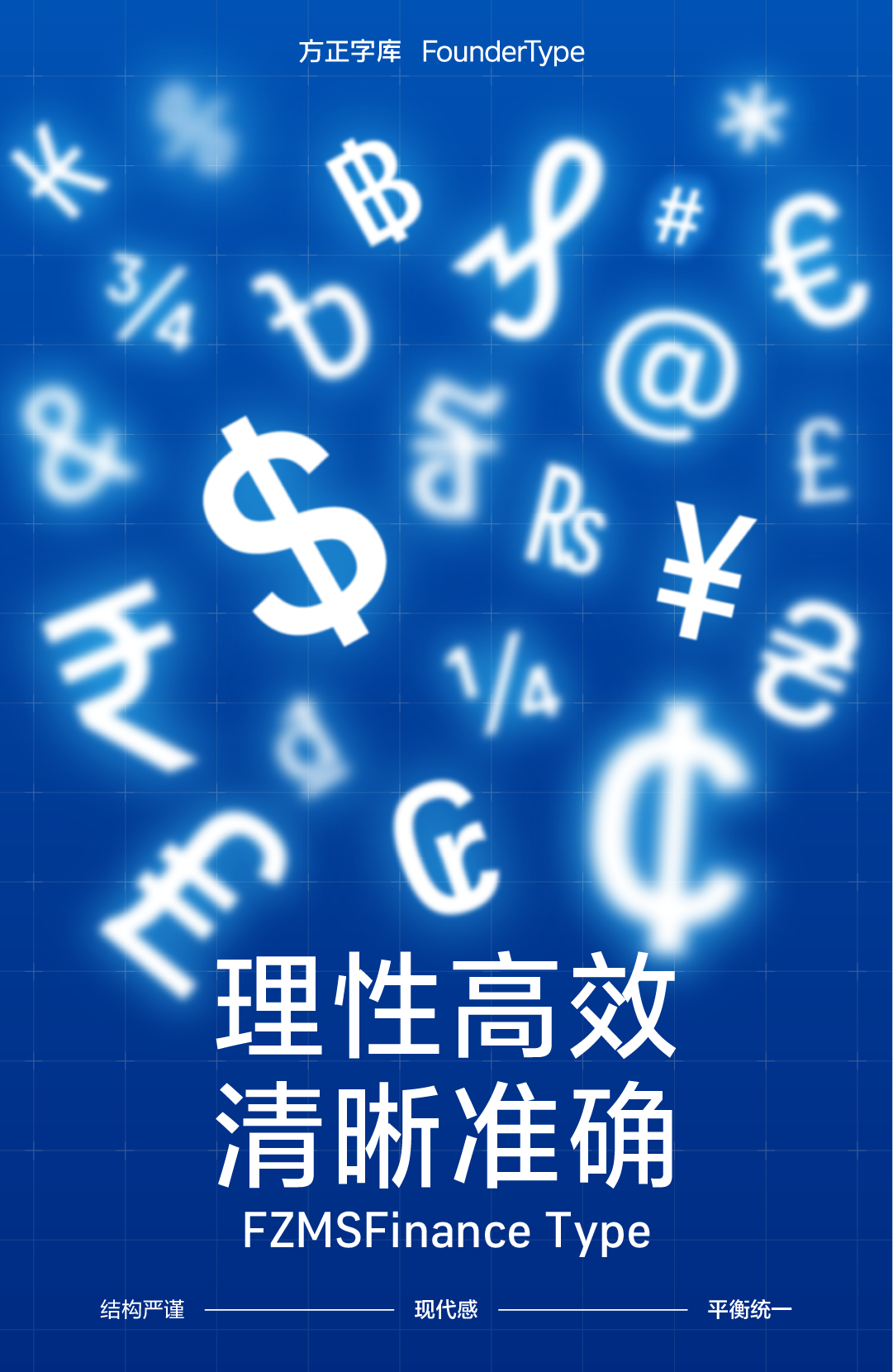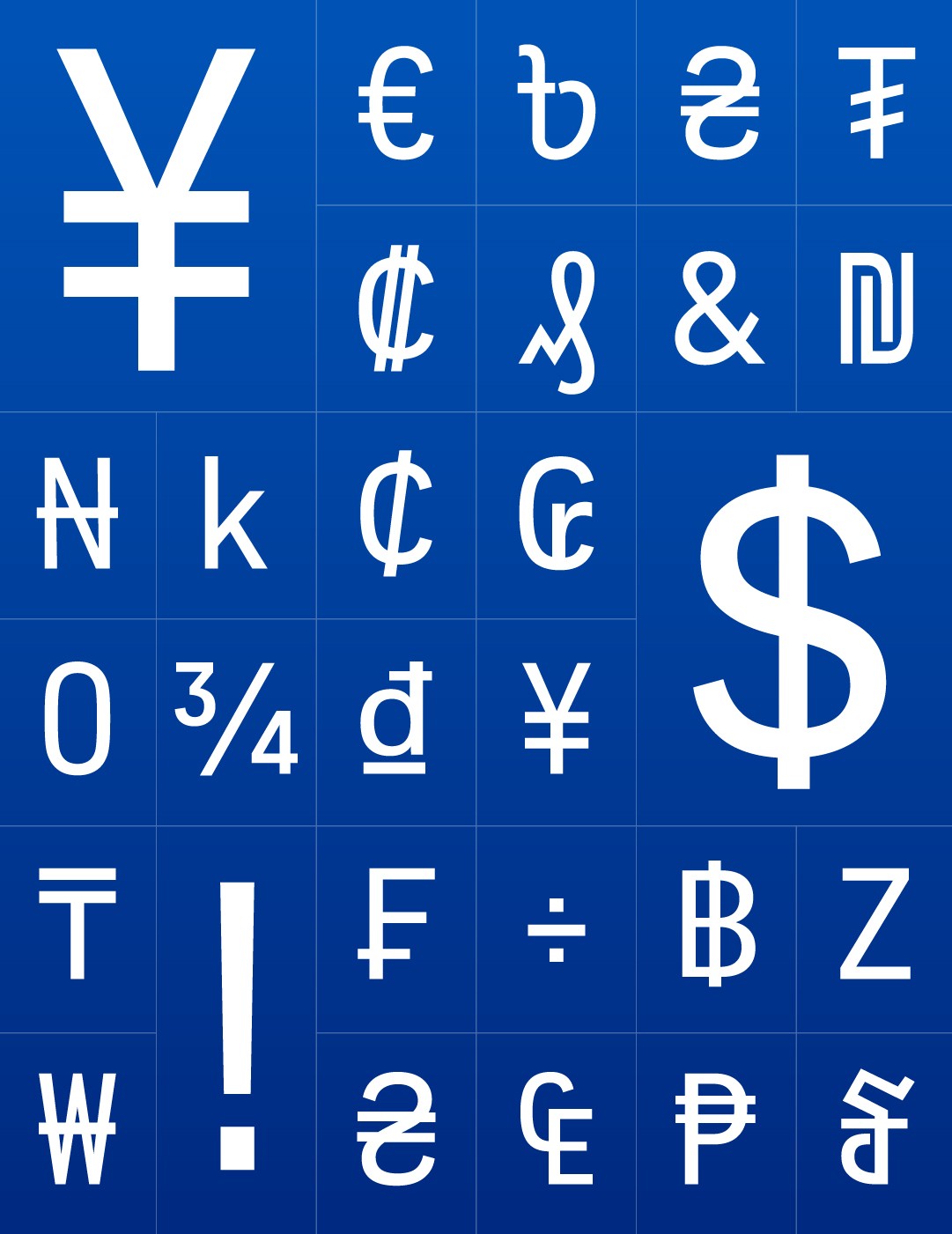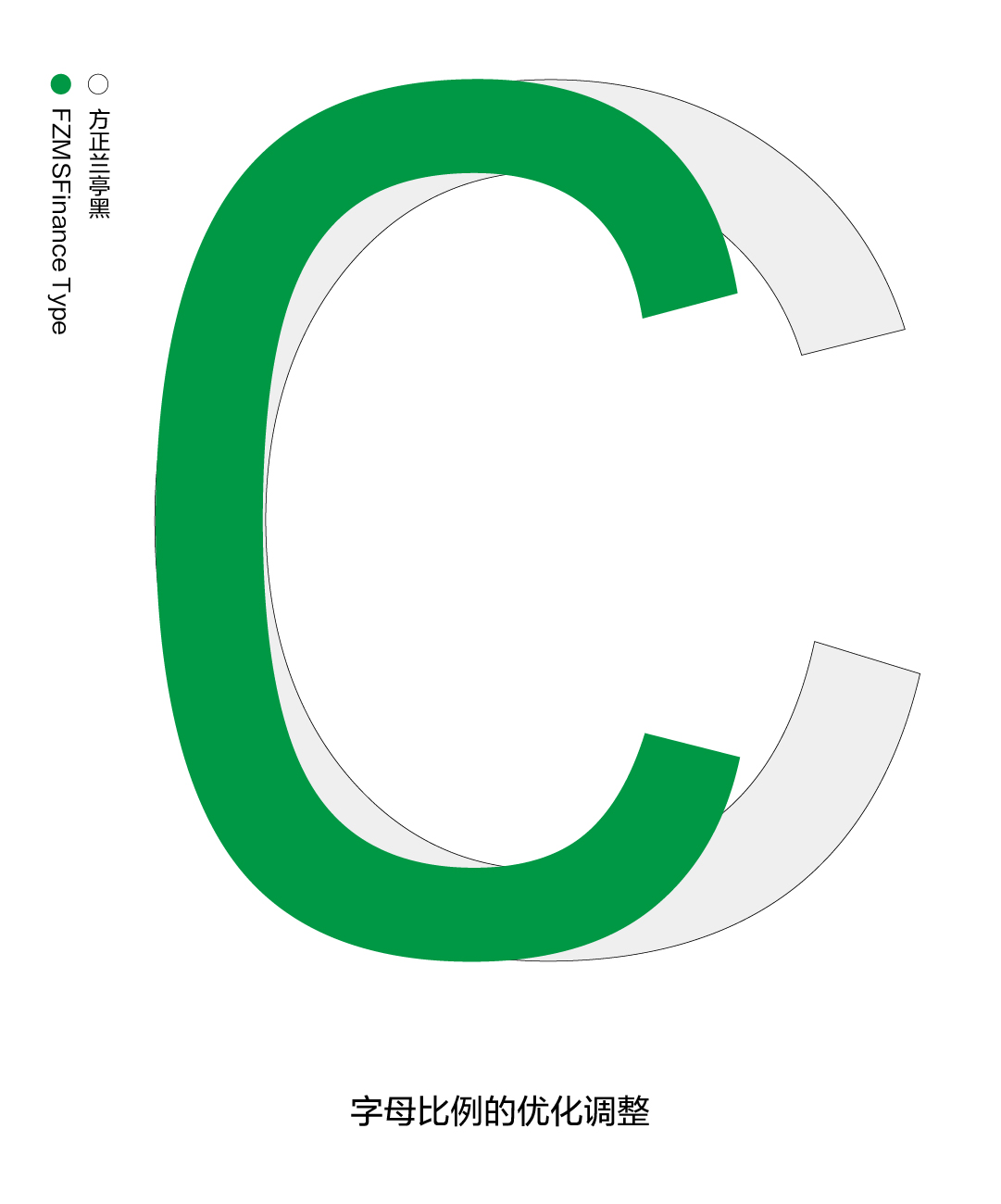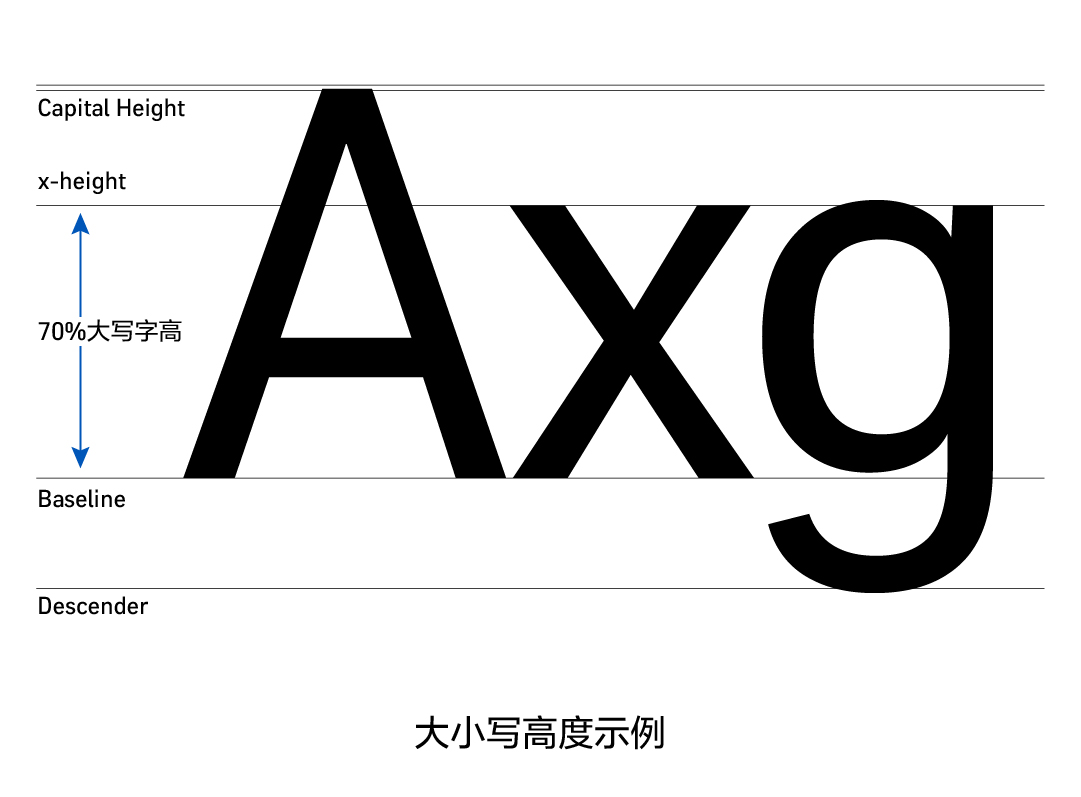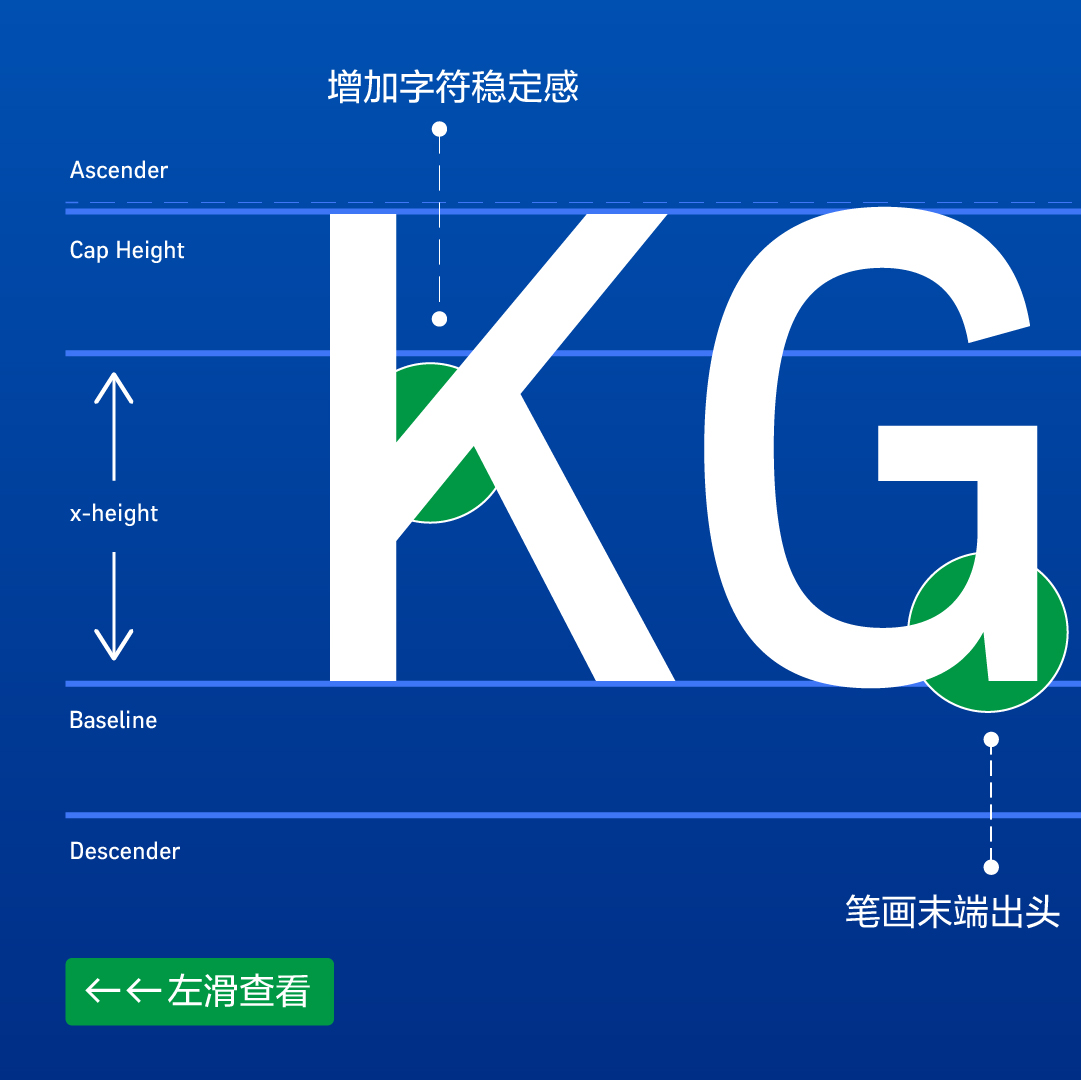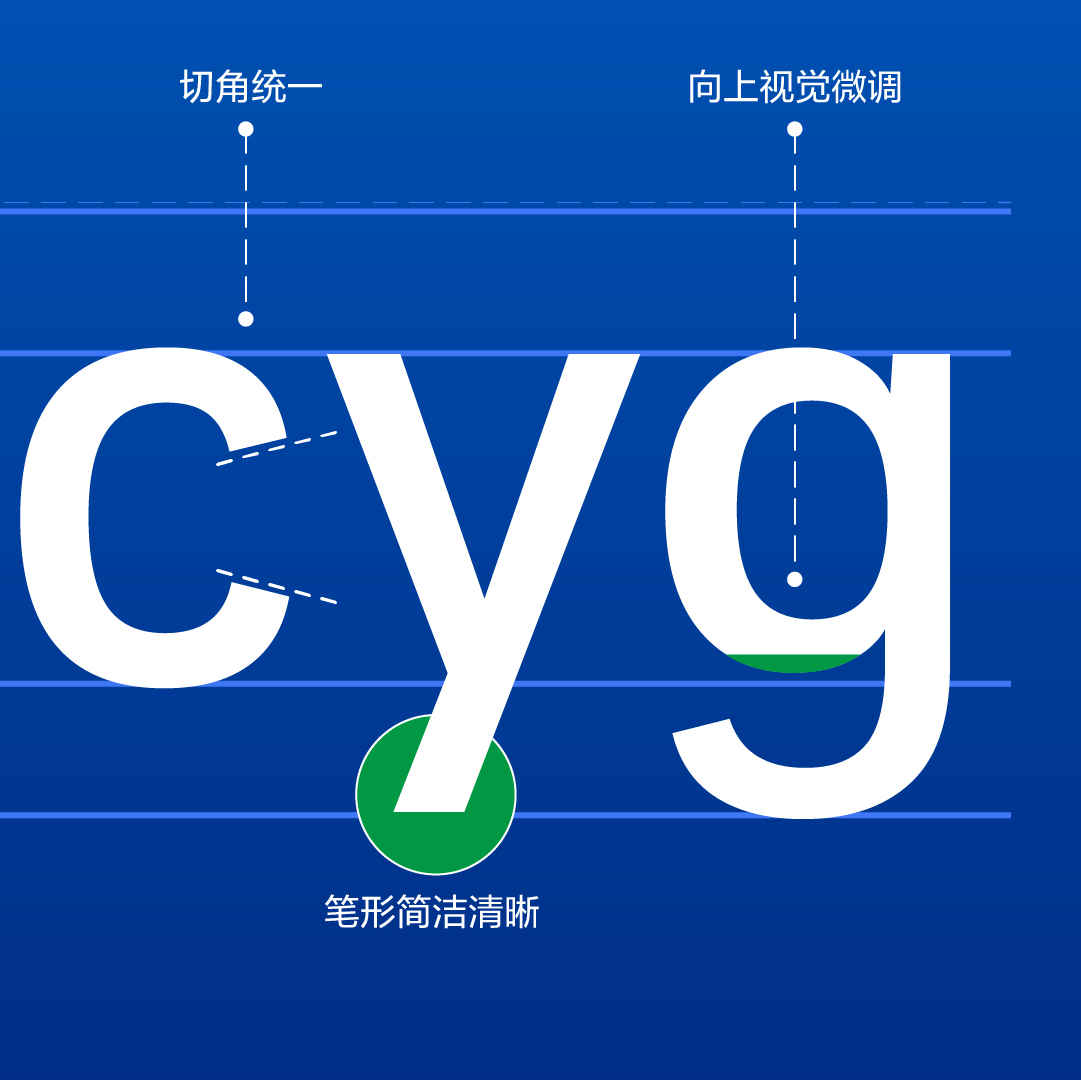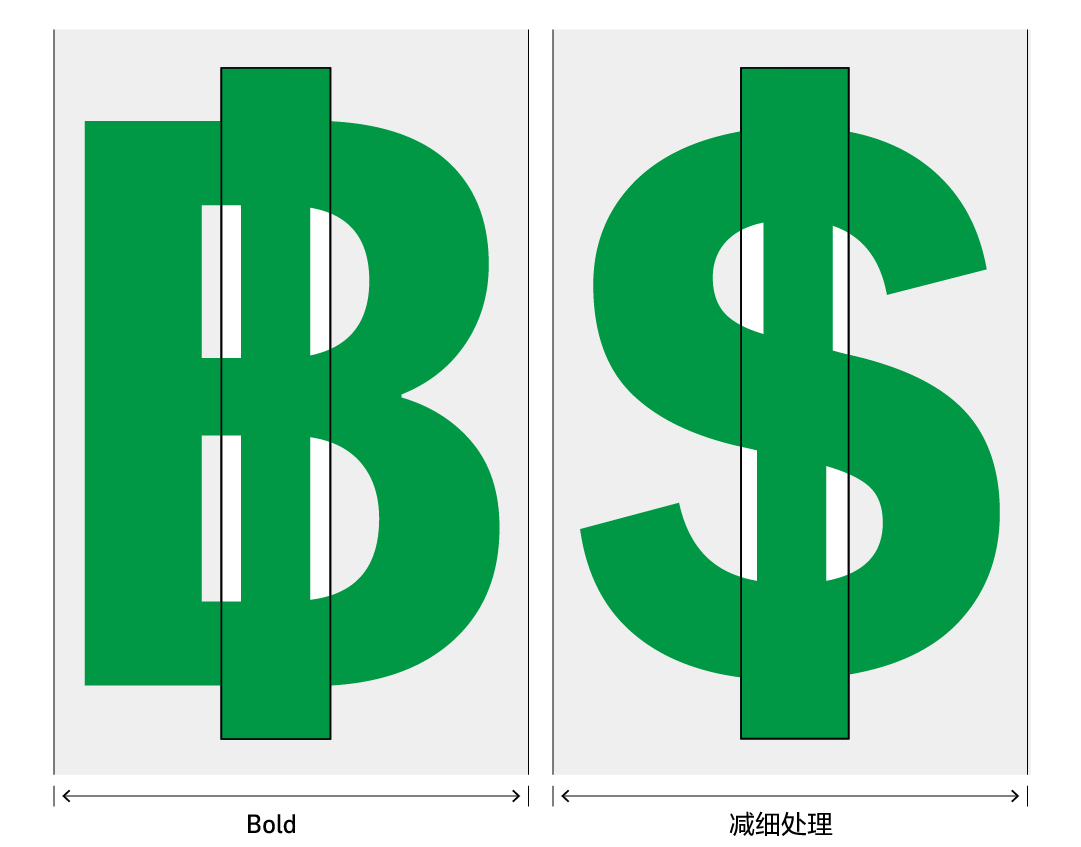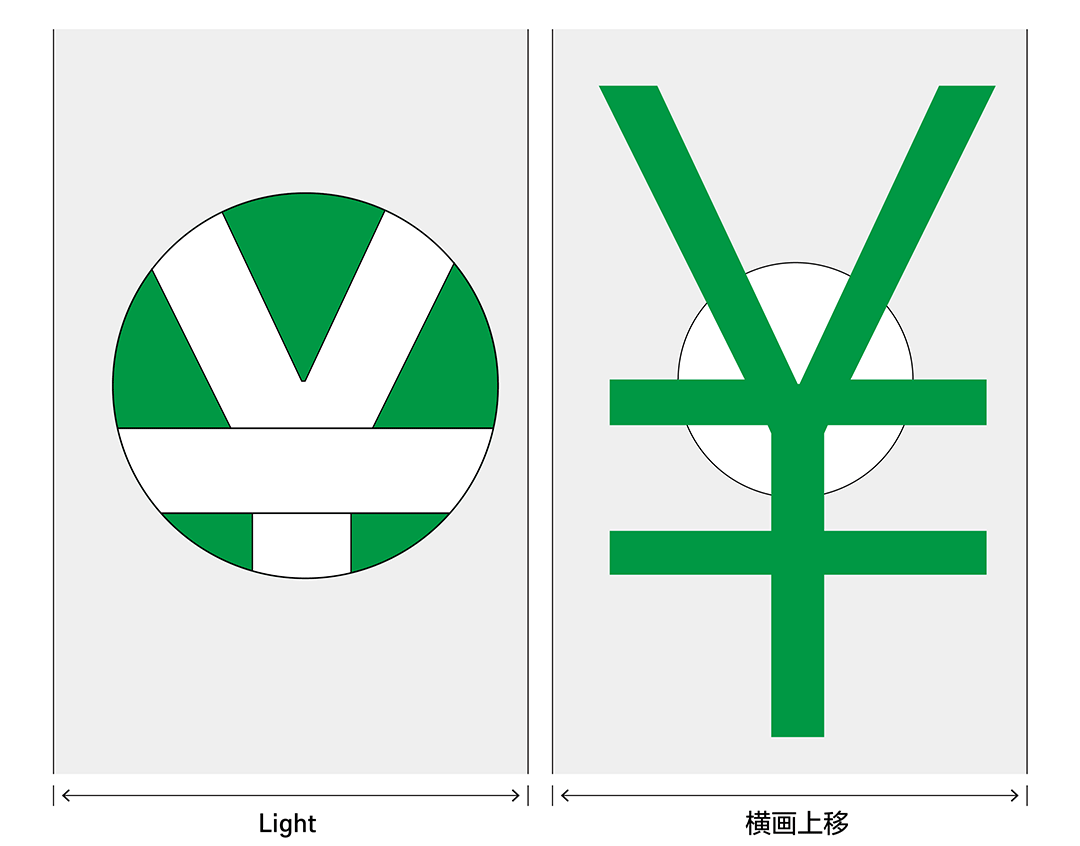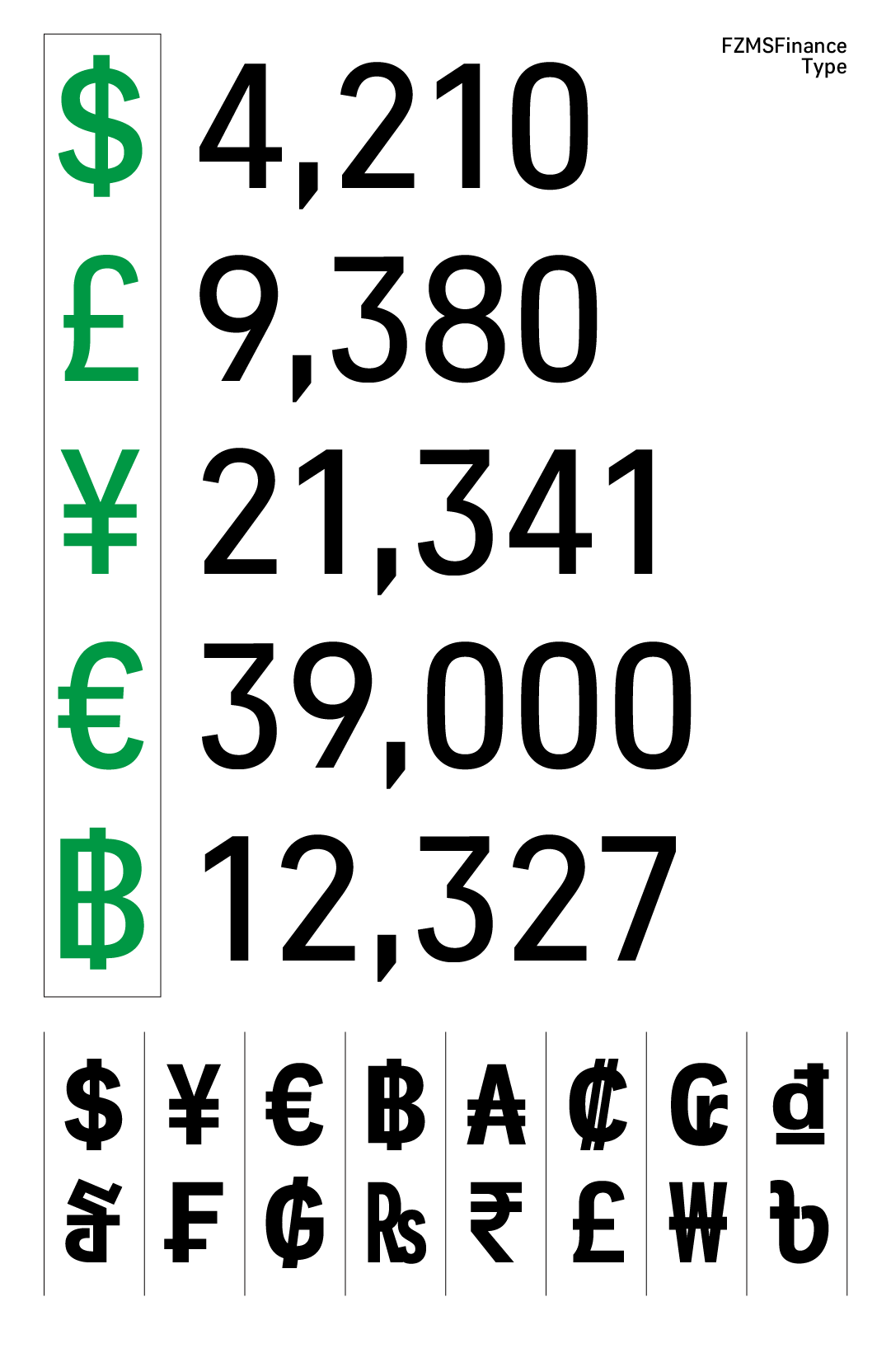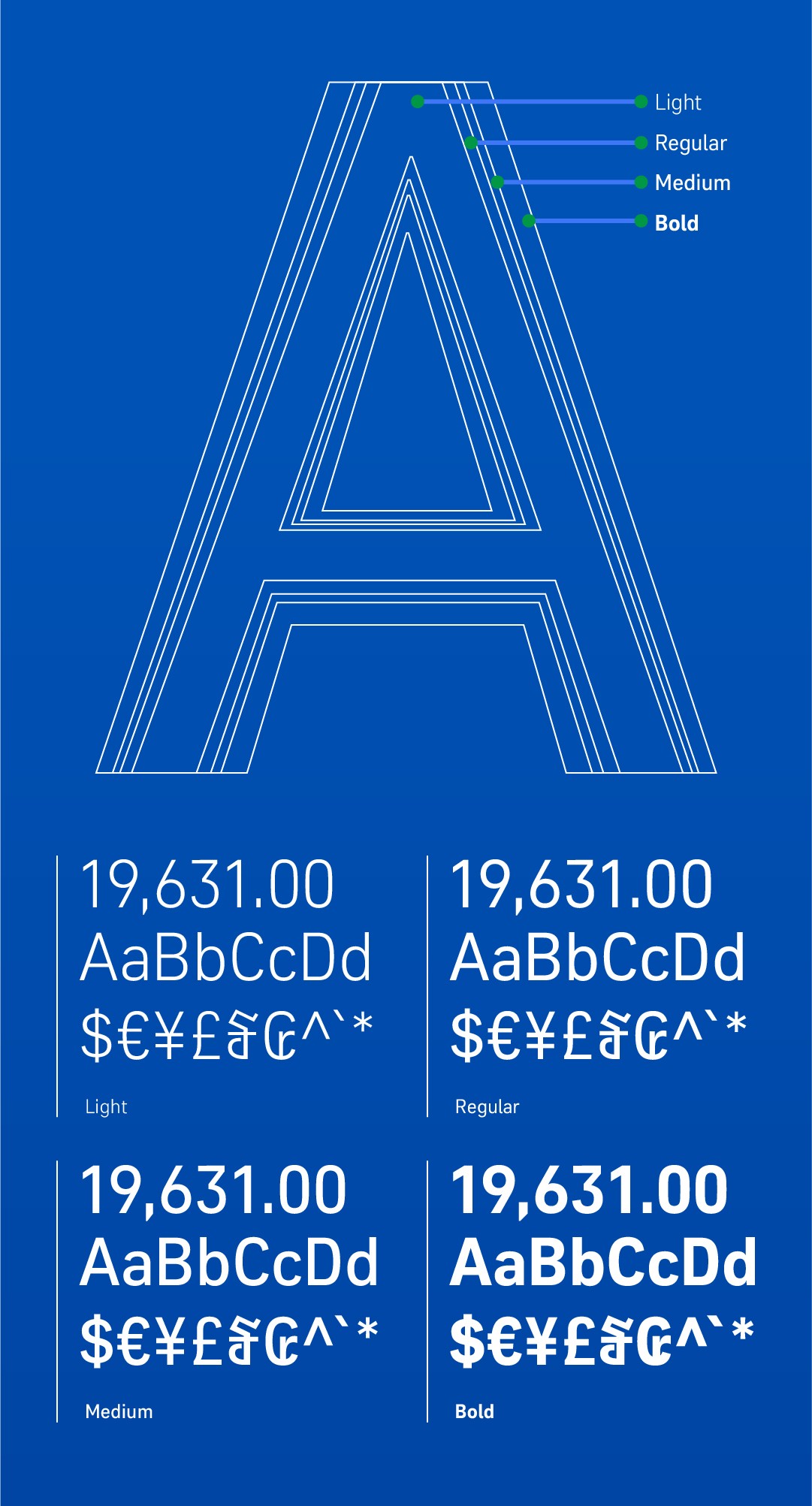
伴随金融行业全面数字化,手机屏幕已成为用户与银行沟通的核心界面。账户余额、转账金额、产品利率、对账明细……海量字符在屏幕上流转。字体看似不起眼,却直接决定了用户能否快速、准确地获取这些关键信息。
方正字库携手民生银行,基于对金融行业的深入洞察,量身打造了一套全新专属定制字体。综合考虑金融行业对信息传达效率、小字号识读准确性及视觉专业感的全面需求,方正字库充分发挥在字体设计与定制领域的专业优势,从屏幕显示的实际场景出发,对字符比例、字号呈现及功能细节进行了系统性的优化设计。
以结构优化保障效率,以人性化细节保障舒适作为设计准则,新字体每一处调整皆针对具体场景,将视错觉因素考虑在内,对宽度进行精细化比例调整,既保留几何结构的严谨,又避免机械死板,建立理性高效的视觉节奏。
精细字宽优化
为了在有限屏幕空间内承载更多有效信息,设计师对 C、G、Y、S 等弧线字母的内部字怀空间与宽度进行了选择性收窄与精细调节。在确保形态识别度的前提下,使字符在排版连续性文本时能形成均匀的灰度,达到视觉上的宽度平衡的同时,又兼顾大字标题下的均衡匀称。在实际应用中,可使手机银行APP的列表页单行容纳更多有效信息,提升了信息获取效率。
高效小字号识读
金融APP中存在大量条款说明、注释信息等小字号文本场景,设计过程中借鉴了小字号可读性的有效经验,针对性地提升了字符的小写x高度与大写字母高度,有效增加字符的可视面积,确保在紧凑空间中字符形态依旧清晰可辨,显著减轻用户辨识负担。
理性克制的几何风格
金融品牌需要传递稳定、精准与专业的气质,字体的视觉基调是塑造这一形象的关键。设计以干净利落的造型为基础,去除多余装饰性笔触,笔画粗细对比克制, 斜向笔画角度经系统化微调,看似对齐的线条实际为照顾圆形与直线及笔画末端的关系进行视觉补正,圆形字母末端切角统一处理,确保风格一致,避免机械印象。细节上,如字母‘g’下降部采取向上的视觉微调,确保密集排列时清晰可辨,从源头避免账号、金额误读,提升文本识别效率。
面向金融的功能定制
数字和符号是金融信息中的核心元素,其呈现的准确性直接影响用户的操作体验。针对金融表格与数据展示的高频场景,协调了所有数字宽度,确保表格中纵向对齐整齐划一,提升数据浏览与比对效率。
货币符号如人民币¥、美元$、泰铢฿等,在形态、粗细与视觉重心上精细处理,确保金额显示、汇率列表等场景中清晰易辨,与数字形成协调统一的视觉组合,避免因符号问题影响信息读取效率。支持高质量中西文混排,完整覆盖基本拉丁、数字及金融常用符号,确保各终端稳定呈现。
方正字库为民生银行定制的这套字体,从金融交互的实际场景出发,通过严谨的结构优化与细腻的细节把控,实现了信息密度、阅读舒适度与视觉专业感的平衡统一。该字体将全面应用于移动应用、网上银行、营销物料及内部系统,成为其数字品牌资产的重要组成部分。